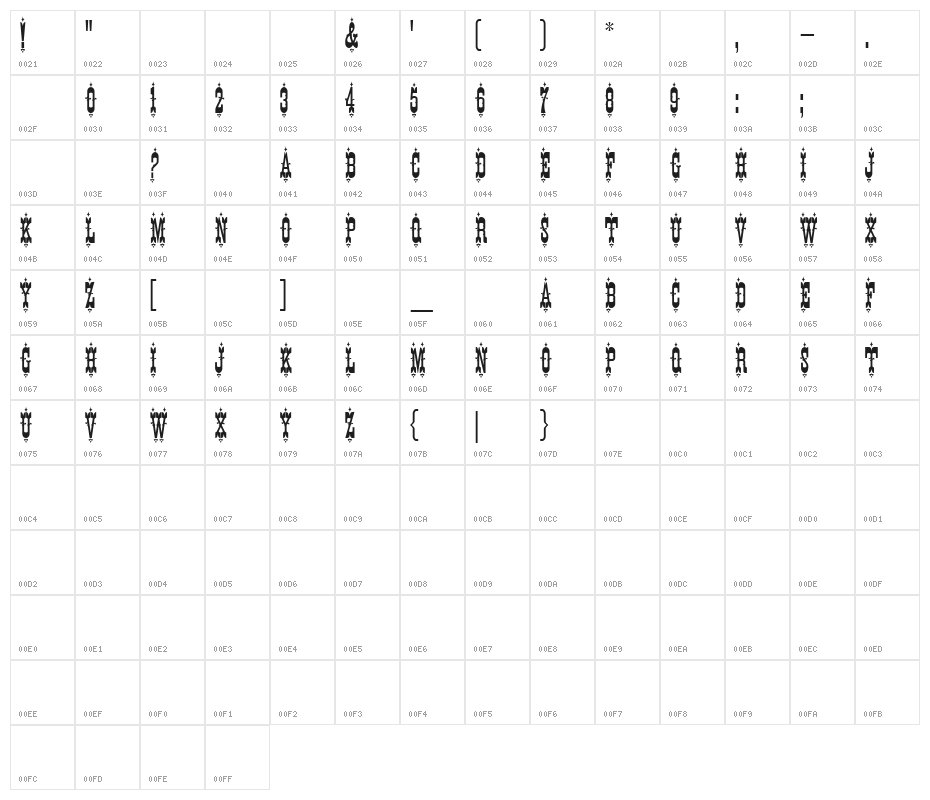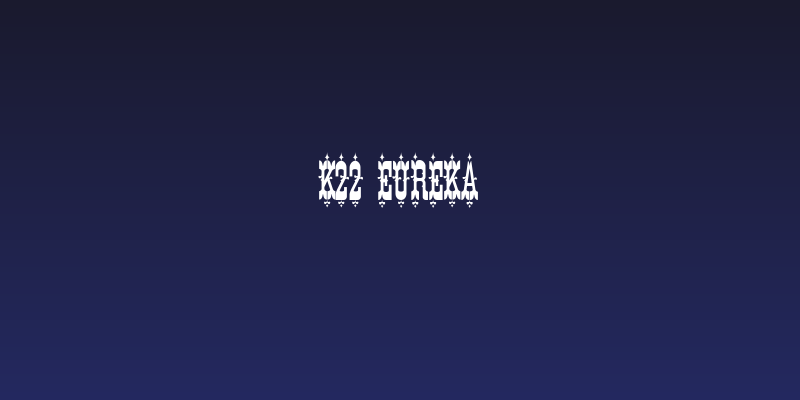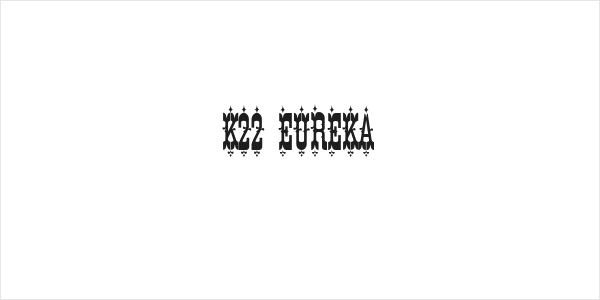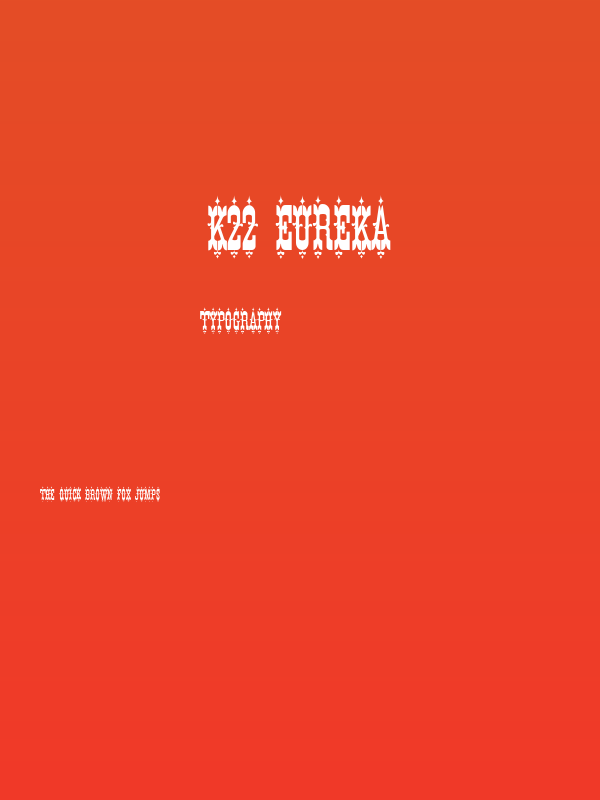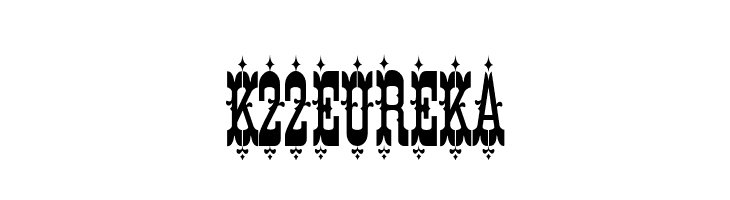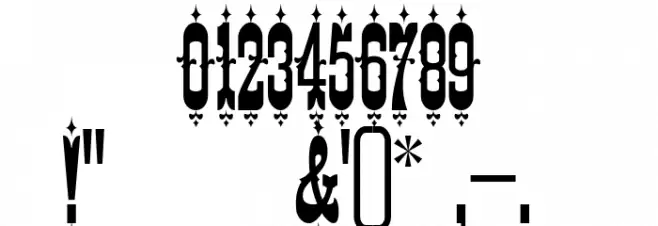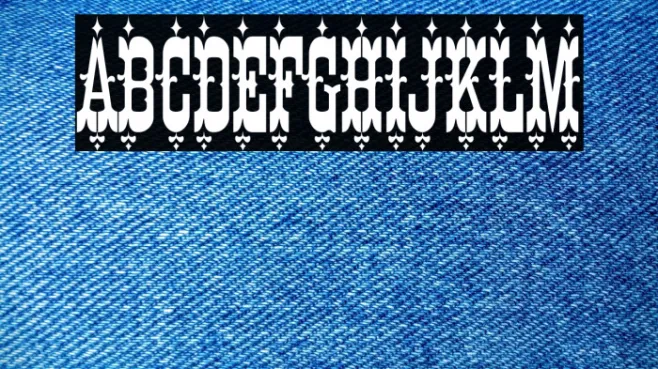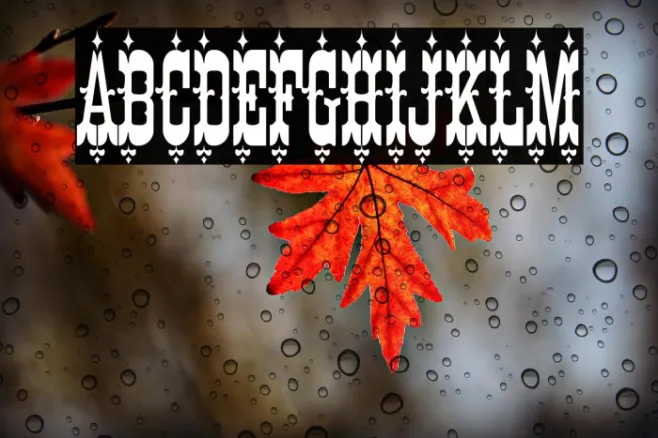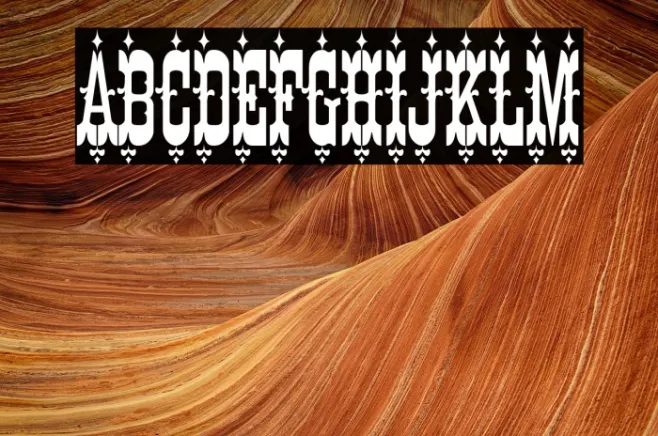
K22 Eureka Font
| Categorías | Retro |
| Estilo general | Vintage |
| Proyectos propuestos | Perfect for posters, event invitations, theatrical productions, and branding that requires a vintage or decorative touch. |